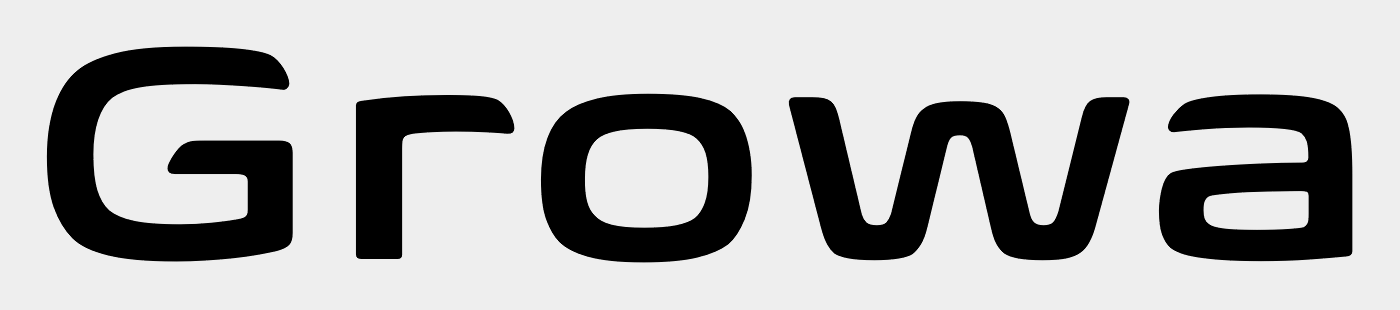
Growag Logo Font
We‘ve developed a complete corporate identity starting from the design of a unique logotype.
Die Aussage lässt vermuten, dass dem Logo keine Satzschrift zugrunde liegt.
So viel zum Thema »unique«. :hammer:
(Und ich fragte mich noch, ob es diese Ink Traps überhaupt gebraucht hätte.)